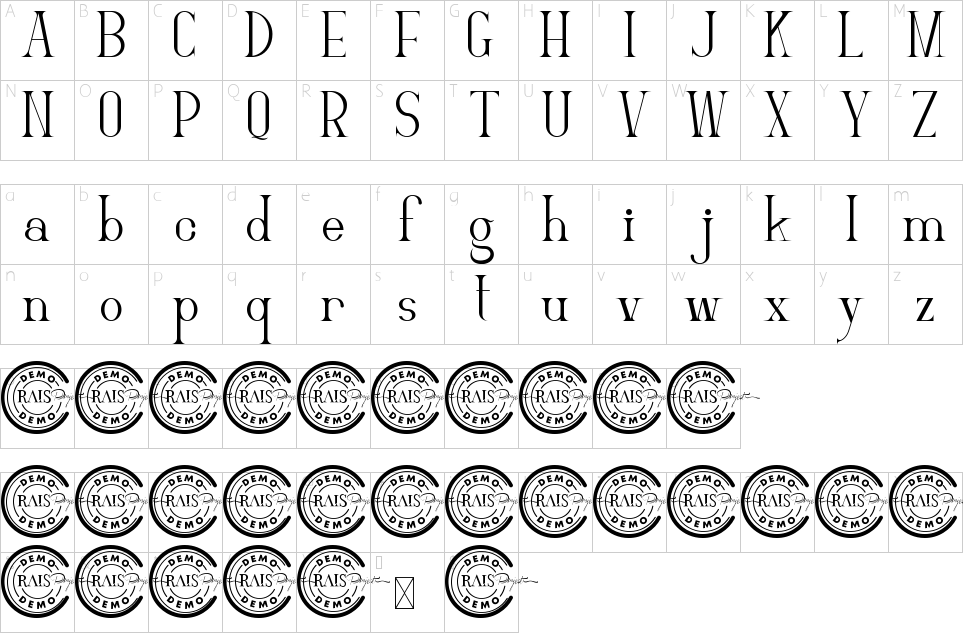
Descubra a Gamiela Font, uma elegante e sofisticada fonte que combina harmoniosamente com diversos estilos de design. Desenvolvida pela RaisProject, essa fonte está disponível gratuitamente tanto para sistemas Windows quanto Mac. Com seu traçado limpo e arredondado, a Gamiela é perfeita para criações de texto moderno e criativo. Com apenas 3.940 downloads ao longo da sua existência, a Gamiela representa um lote limitado de qualidade gráfica que merece ser explorada. Esta fonte adiciona um toque especial à sua próxima peça de design, seja ela uma simples assinatura digital ou um trabalho de arte mais complexo. Não perca essa oportunidade para adicionar autenticidade e estilo a suas criações digitais com Gamiela Font.